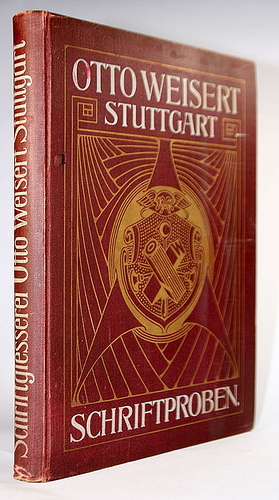
Schrift aus Katalog Otto Weisert ca 1890
Ich habe aus einem alten Otto Weisert Katalog die Beschriftung der fonts gesehen und suche jetzt die Schriftart, um entsprechend arbeiten zu können.
Kann mir da jemand helfen?
So fallen mir nur ein paar ähnliche Kandidaten ein, wie z.B. die Ringlet von MacKellar, Smith & Jordan oder die Ancienne von Stempel.
Suchst Du denn eine ähnliche digital Version für die Arbeit, oder genau die alte Entsprechung?
@ Lars: Die genaue Entsprechung wäre ideal, es tut aber auch eine digitale Version. Die vorgeschlagenen Schriften sind leider nicht ähnlich genug. Ich hätte nie gedacht, dass es eine derartige Vielfalt gibt...